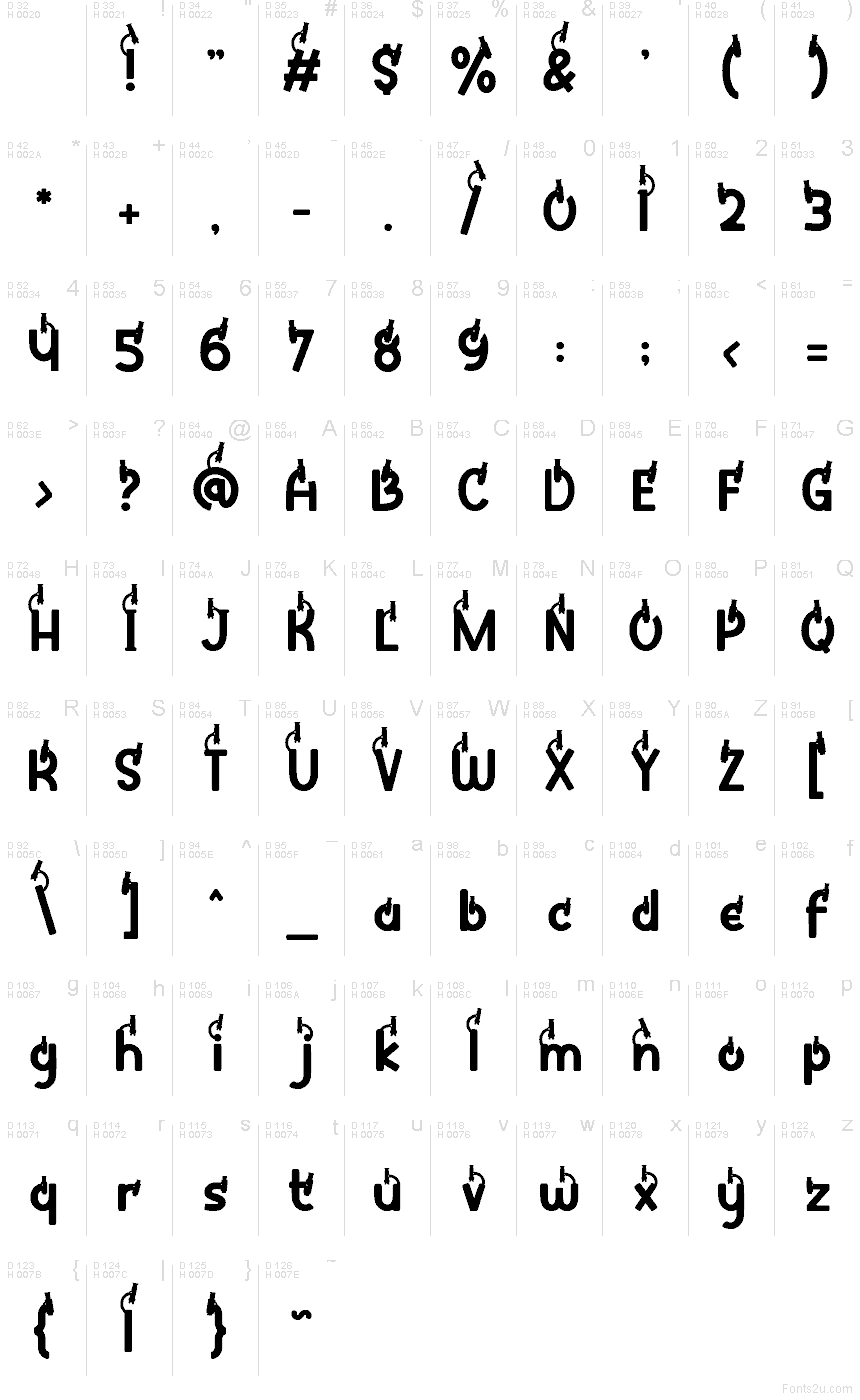
Clever Science Mircoscope
Clever Science Microscope, eine kostenlose, wissenschaftlich orientierte Display-Schrift von Putracetol Studio, verwandelt kräftige Kleinbuchstaben in ein kleines Labor voller Mikroskop-Silhouetten und geschwungener Instrumentenformen. Die abgerundeten, massiven Buchstaben wirken spielerisch statt klinisch, während sich die Mikroskop-Details durch das gesamte Alphabet ziehen und ein stimmiges Gesamtbild rund um das Thema Schulwissenschaften erzeugen.
Diese kostenlose Schrift eignet sich perfekt für Schulplakate, Flyer für MINT-Veranstaltungen, Arbeitshefte für Kinder, Ausstellungen bei Wissenschaftsmessen oder YouTube-Titelbilder, bei denen ein visueller Wiedererkennungswert entscheidend ist. Da die Buchstaben das Mikroskop-Motiv bereits in sich tragen, ohne dass zusätzliche Illustrationen erforderlich sind, ist sie ideal für kurze Überschriften, badge-artige Logos und Titel zu biologischen Themen oder Laboraktivitäten.